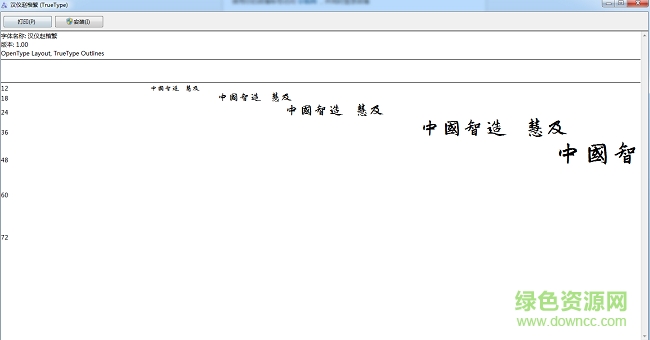
漢儀趙楷繁
漢儀趙楷繁字體是一款非常漂亮的繁體字體,該字體線條流暢靈動,筆畫處理適宜,結(jié)構(gòu)緊密不渙散,字形美觀,用途廣泛,喜歡的朋友快來綠色資源網(wǎng)下載吧!
楷書字體介紹
楷書也叫正楷、真書、正書。從程邈創(chuàng)立的隸書逐漸演變而來,更趨簡化,橫平豎直,結(jié)構(gòu)疏密得當(dāng),則退而寫小楷可做到結(jié)體寬綽開張,點畫規(guī)矩清楚!
漢儀趙楷繁
楷書發(fā)展歷程
即楷書的萌芽期——秦漢,楷書發(fā)展期——魏、晉、南北朝,楷書繁榮期——隋、唐、五代,楷書守成期——宋、元、明、清。